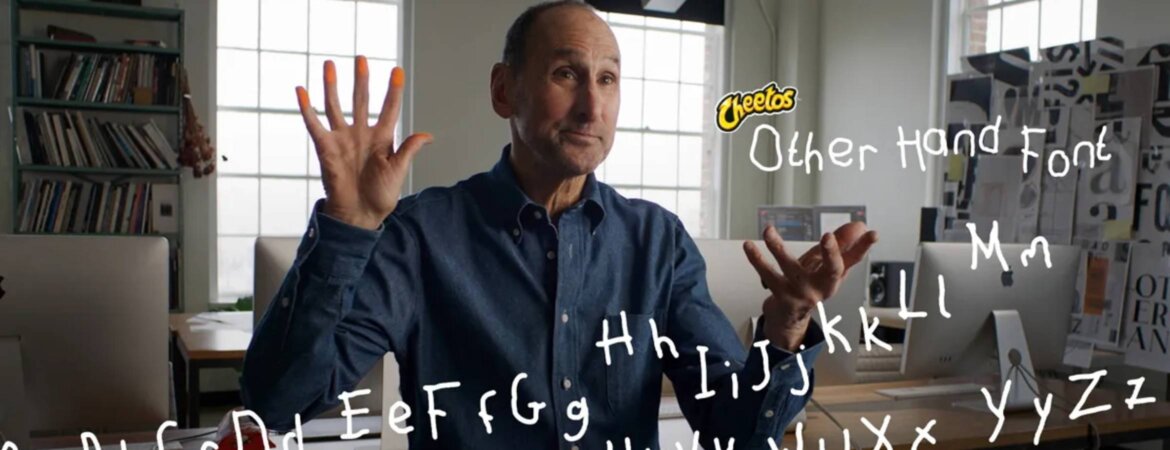
Quand le snacking inspire le design.
Cheetos, la célèbre marque de snacks au fromage, pousse encore plus loin l’art de célébrer son iconique résidu de poudre orange, le Cheetle. Pour l’occasion, la marque dévoile “The Other Hand Font”, une police d’écriture volontairement maladroite, créée avec la main non dominante. Une idée originale qui s’inscrit dans la campagne “The Other Hand”, célébrant la réalité cocasse des fans de Cheetos : une main recouverte de Cheetle, l’autre tentant de mener les activités quotidiennes.
Conçue par Goodby Silverstein & Partners, l’agence derrière certaines des campagnes publicitaires les plus marquantes de Cheetos, cette police a été imaginée avec une touche d’autodérision. Rich Silverstein, cofondateur de l’agence et légende de la publicité, a lui-même participé au projet, en utilisant uniquement sa main non dominante. Le résultat ? Une typographie qui mêle maladresse et créativité.
Lancée à l’occasion de la Journée nationale de l’écriture manuscrite (le 23 janvier), cette initiative illustre une tendance grandissante des marques à embrasser leurs imperfections.
The Other Hand Font n’est pas qu’une blague, c’est une extension de l’univers espiègle de Cheetos. En jouant avec l’idée d’imperfection, la marque invite ses consommateurs à ne pas se prendre au sérieux, tout en célébrant leur passion pour le snacking. Alors, pourquoi rester dans la sobriété d’un Times New Roman quand on peut signer ses emails avec une touche de Cheetle ?